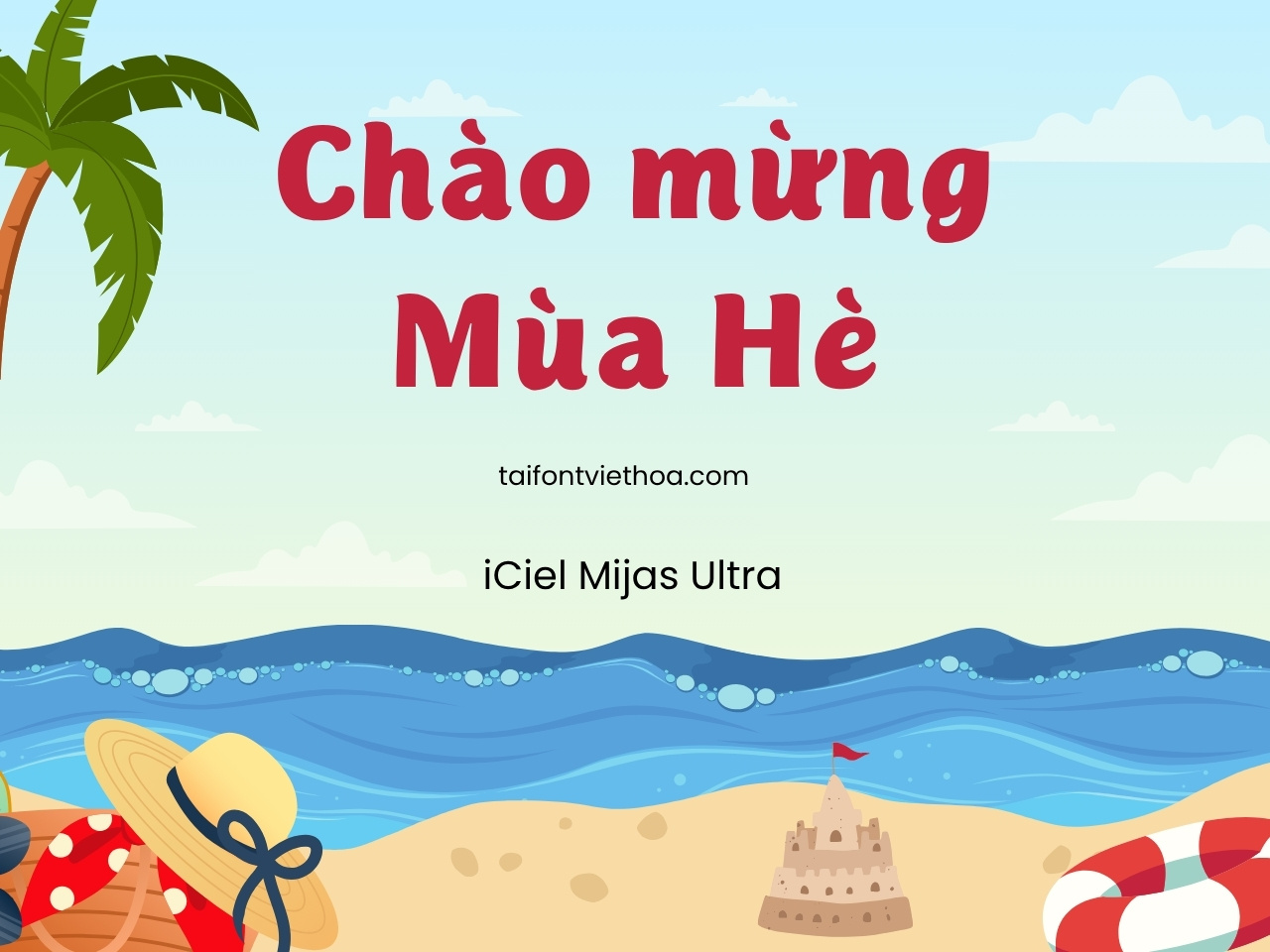
Giới thiệu về font iCiel Mijas – Ultra – Mạnh mẽ, hiện đại và đầy tính thương hiệu
iCiel Mijas – Ultra là một kiểu chữ sans-serif mang phong cách hiện đại, nổi bật với độ đậm cực cao (ultra bold), giúp tạo nên sự tương phản mạnh mẽ và điểm nhấn rõ rệt trong thiết kế. Phiên bản Việt hóa do iCiel thực hiện, hỗ trợ đầy đủ tiếng Việt cùng hơn 60 ngôn ngữ khác, mở rộng khả năng ứng dụng cho các chiến dịch thiết kế toàn cầu, từ branding chuyên nghiệp đến truyền thông số.
Font được taifontviethoa.com tuyển chọn và giới thiệu như một giải pháp tối ưu cho những ai đang tìm kiếm kiểu chữ thương hiệu mạnh, rõ ràng và đầy cá tính. Với độ dày lớn và hình dáng chắc chắn, iCiel Mijas – Ultra dễ dàng thu hút ánh nhìn, đặc biệt trong các thiết kế tiêu đề, poster, bảng hiệu hay bao bì sản phẩm cần sự nổi bật ngay lập tức.
Đặc điểm thiết kế và ứng dụng của font iCiel Mijas – Ultra
Mijas – Ultra có cấu trúc chữ hình học rõ nét, phần thân chữ rộng và độ cao đồng đều giúp tối ưu khả năng đọc ở mọi kích cỡ. Đặc điểm ultra bold khiến từng chữ cái trở thành một khối vững chắc, mang lại cảm giác tin cậy, chuyên nghiệp và cực kỳ hiệu quả khi sử dụng cho thương hiệu, tiêu đề hoặc các ấn phẩm quảng cáo cần tạo điểm nhấn trực quan.
Font này đặc biệt phù hợp với các ngành nghề như công nghệ, bất động sản, thiết kế thương hiệu, truyền thông số, thể thao hoặc startup hiện đại. Một số ứng dụng tiêu biểu gồm: thiết kế logo mạnh mẽ, banner quảng cáo, poster sự kiện, giao diện ứng dụng, bảng hiệu, tiêu đề website hoặc các dự án yêu cầu tính hiện đại, nổi bật và đầy quyền lực trong hình ảnh thị giác.